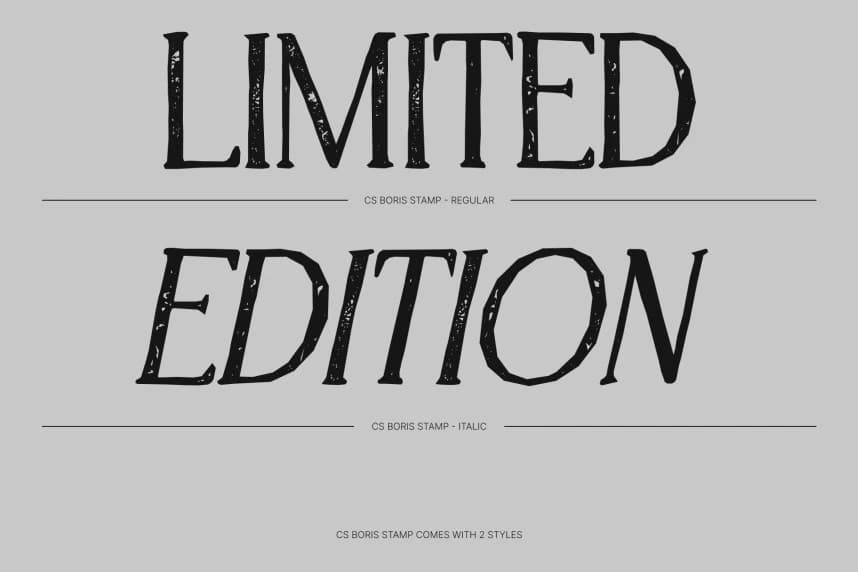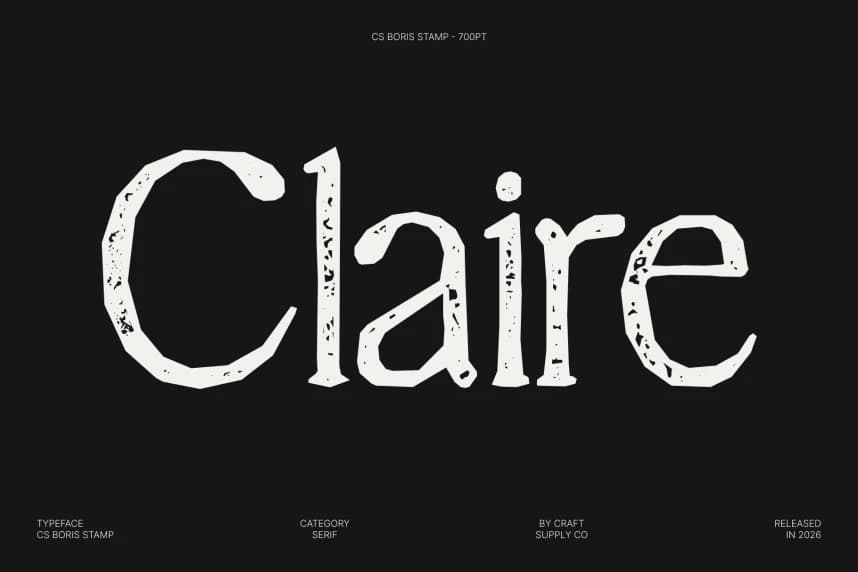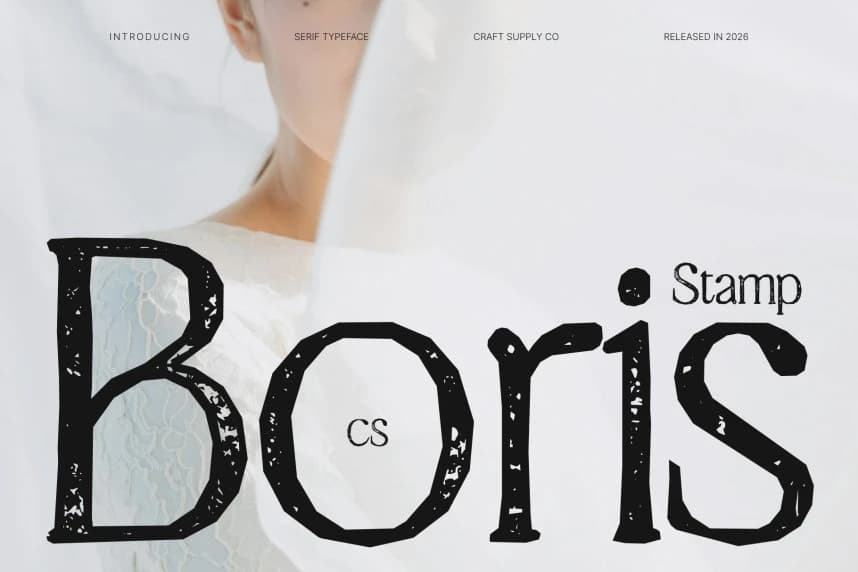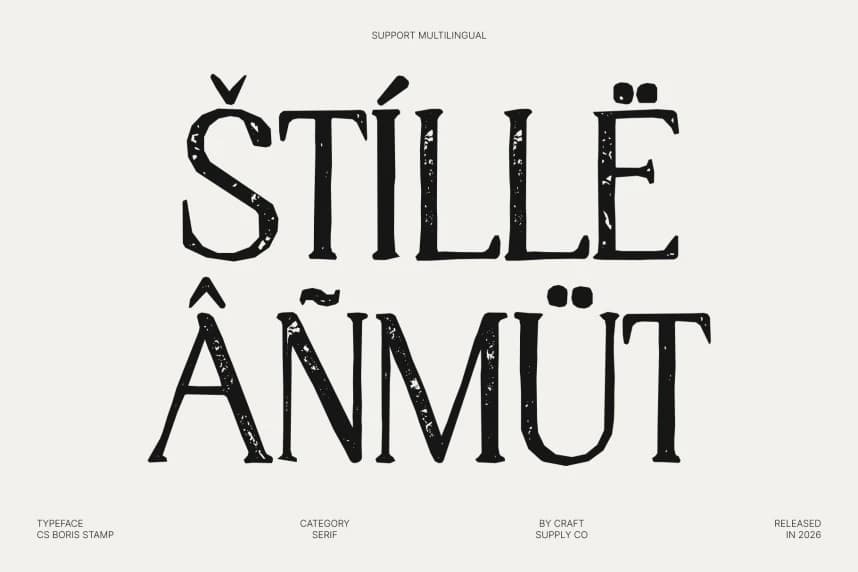
CS Boris Stamp Font
CS Boris Stamp Font – Doku Sofistikasyonuyla Zarif Serif. Damgalı bir izle zarafeti rafine eder. Bu, zarif yapısına ince damgalı bir doku ekleyerek modern serif güzelliğini yeniden tanımlıyor.
CS Boris Stamp Font – Doku Zenginliğine Sahip Zarif Serif. Damgalı İziyle Sofistike Zarafet. Bu, zarif yapısına ince damgalı bir dokuyu ekleyerek modern serif güzelliğini yeniden tanımlar.